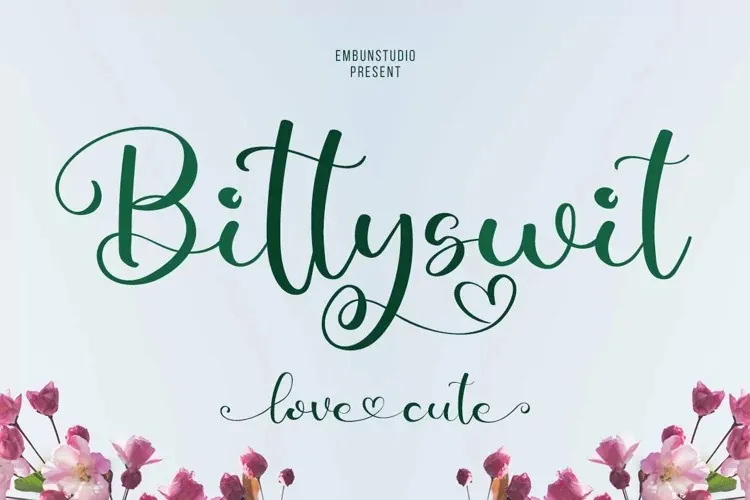
A Bittyswit Font é uma elegante tipografia de calligrafia criada pela Embun Studio, com letras que dançam ao longo da linha base, oferecendo um toque de luxo e sofisticação a qualquer projeto de design que você possa criar. Esta fonte contém PUA encodadas, o que significa que todos os seus amadurecidos gílios e ligaturas podem ser acessados com facilidade, tornando-a perfeita para aqueles projetos especiais onde um toque a mais de sofisticação é desejado. Uma opção ideal para designers em busca de uma tipografia refinada que ofereça uma pitada romântica e saborosa ao trabalho de design.